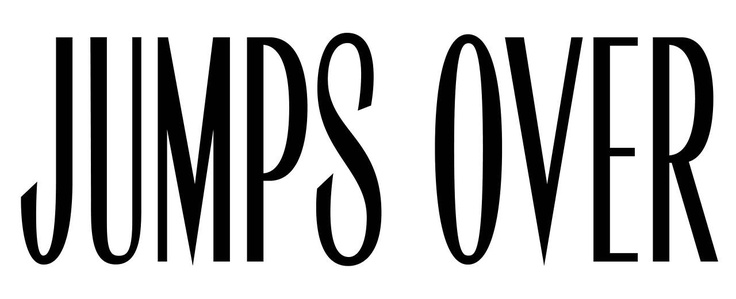
Немаловажную роль в создании дизайна макета играет правильный подбор шрифтов. В настоящее время существует огромное количество шрифтов и их число постоянно увеличивается. У каждого из них есть собственное название, например «Arial», «Times» и др. Для удобства, связанные шрифты группируют в семейства, например «Serif», «Times», «Futuris»… шрифтовые семейства включают различные начертания, отличающиеся друг от друга насыщенностью (легкий, обычный, жирный) и стилем (романский, курсив, суженный). Большинство семейств делится на 2 основные группы: serif (с засечками) и san-serif (без засечек), и есть еще множество рукописных, декоративных и необычных шрифтов на любые случаи жизни. При оформлении текста, в погоне за красотой и оригинальностью, не стоит забывать о его восприятии и читабельности.
До того как печать стала компьютеризированной — литейные цеха выпускали каждый знак в полном ассортименте размеров, каждый конкретный размер шрифтового начертания назывался шрифтом.
Размер шрифта измеряется в пунктах, а точнее, его высота. (Пункт — это мельчайшая единица измерения в полиграфии, 72 пункта составляют дюйм.) Эта система измерения возникла в 18-м веке, когда шрифты изготавливались из металла и дерева и были стандартных размеров (9, 10, 12, 14, 16, 18, 24, 30, 36, 48, 60, 72). Любопытно, что в те давние времена размер шрифта соответствовал не размеру печатного знака, а величине наборного блока, содержащего этот знак, поэтому шрифты одного размера могут визуально отличаться по размеру символов.
Над этим сложным вопросом ломают голову не только дизайнеры, а еще и психологи, которые провели немало исследований на эту тему. Согласно этим исследованиям, один и тот же текст, написанный разными шрифтами, может вызывать разные эмоции. Используемые шрифты должны не только гармонировать с общим оформлением макета, но и соответствовать характеру рекламируемого товара или услуги.
Выбор шрифтов так же зависит от того, где будет отображаться текст: на экране монитора и на бумаге текст воспринимается по-разному.
Самые популярные и распространенные — нейтральные прямые шрифты, немного вытянутые по вертикали. Такой тип шрифтов, в основном, используют в оформлении официального текста.
Чтобы произвести серьезное и авторитетное впечатление, обычно используют строгие квадратные шрифты, ими выделяют важную информацию. Такие шрифты часто используются в дизайне рекламы и фирменном стиле промышленных компаний, в заголовках новостных газет.
Округлые шрифты вызывают ощущение легкости, спокойствия и уюта.
Наклонные шрифты делятся на 2 вида: курсивные и рукописные. Текст набранный курсивом воспринимается менее важным, по сравнению с текстом, который набран прямым шрифтом. Наклонные шрифты обычно используются для оформления примечаний и менее важной либо неофициальной информации. Курсивными и рукописными шрифтами часто оформляют вывески и рекламу салонов красоты, кондитерских, магазинов для женщин и там, где нужно подчеркнуть легкость, изящество и красоту.
Читабельность наклонных шрифтов уступает прямым, поэтому при разработке рекламных макетов для билбордов и другой наружной рекламы, по возможности, лучше воздержаться от их использования, особенно при небольшом размере шрифта.
Декоративные шрифты в оформлении шрифты имеют не только визуальное, а и смысловое предназначение. Стилизованные обычно сложно читать, поэтому использовать их нужно с осторожностью и только там, где их применение обосновано, например, для передачи и усиления определенной атмосферы.
Кстати, шрифты по-разному воспринимаются мужчинами и женщинами. Для рекламы рассчитанной на мужскую аудиторию предпочтительнее использовать прямые строгие шрифты. Женской половине более привлекательны шрифты с округлыми формами.
Почему шрифт — важный элемент в рекламе, и при чем тут арбитраж
Содержание
Шрифт — влиятельная вещь, которая воздействует на восприятие текста, а значит имеет немаловажное значение в рекламе товаров и услуг. Если нам не нравится внешний вид текста, мы можем вовсе его проигнорировать.
Какие шрифты привлекают внимание, и есть ли свой шрифт арбитража — читайте в нашем материале.
Шрифт — это элемент айдентики, одна из ключевых частей фирменного стиля компании. Существуют бесплатные и платные шрифты, а еще кастомные, которые компании разрабатывают сами для себя. Ниже мы будем рассматривать ценность именно кастомного шрифта, поскольку его разработка требует немалых ресурсов, и люди задаются вопросом «Ради чего? Это же просто шрифт». Но это далеко не так.
Какие функции выполняет кастомный шрифт? Прежде всего он создает бренду уникальный образ и выделяет его среди конкурентов. Он отображает характер компании на разных площадках, как онлайн, так и офлайн. Хорошо проработанный шрифт помогает выработать единый стиль у компании, ту самую айдентику. И немаловажно, что он помогает бороться с недобросовестными конкурентами, которые не гнушаются использовать чужую марку и подгонять оформление своего товара под стиль другого уже востребованного бренда (вспомните, как часто мы видим вывески «Шаурма», стилизованные под McDonald’s).
Но полностью скопировать кастомный шрифт трудно, и отличия все равно можно заметить.
Компании необязательно полностью разрабатывать шрифт для всего алфавита, можно ограничиться несколькими буквами только для лого. Но крупные бренды с большими бюджетами не жмутся и могут позволить себе создать целые шрифтовые системы: например, Apple сделали для себя шрифт San Francisco, Microsoft — Segoe, а Google сразу два — Product Sans и Roboto.